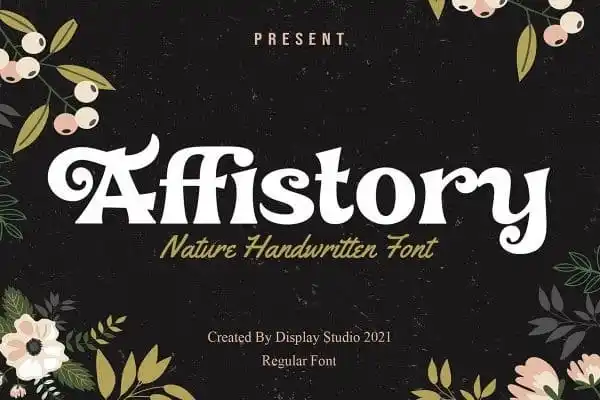
Affistory Display Font – Download Grátis
A Affistory Display Font é uma escolha perfeita para aqueles que buscam uma fusão única e intrigante entre a elegância dos padrões serifados clássicos e as personalidades vibrantes das letras de revista vintage. Inspirada nos tempos do cinema mudo, esta fonte exibe um estilo atemporal e sofisticado, perfeita para branding, cartas de convite, cardes de agradecimento ou qualquer projeto que seja sobre expressar sua personalidade. Com a capacidade incrível de suportar múltiplas línguas, esta fonte oferece um grau extra de flexibilidade e versatilidade, tornando-a ideial para projetos internacionais. Seu estilo variado também permite que você personalize suas aplicações, adaptá-las à sua própria identidade visual sem sacrificar o equilíbrio elegante do design. Seja em um evento formal ou em uma comunicação digital casual, a Affistory Display Font trará seu trabalho para vida e adicionará um toque de sofisticação que será recordado. Não espere mais para dar vida à sua marca com esta fonte poderosa.